Fonty - anatomia
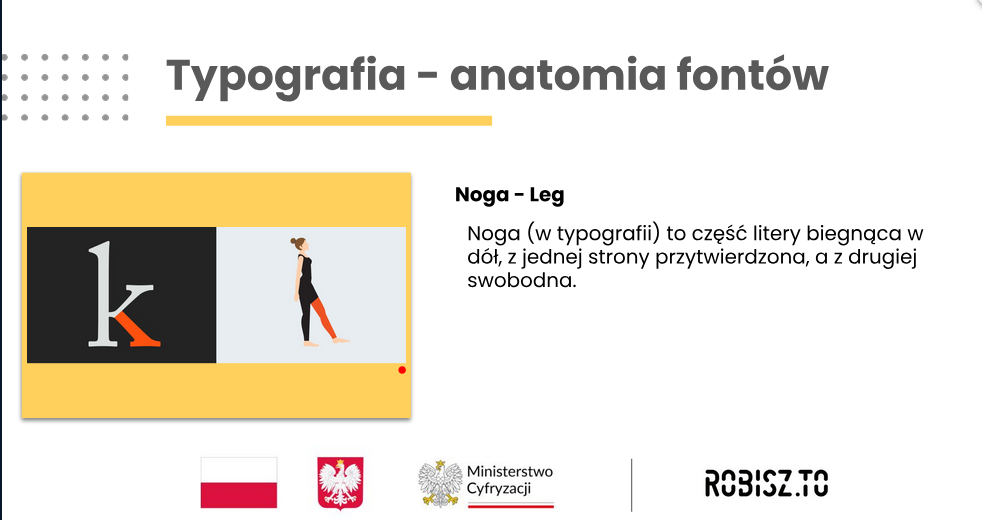
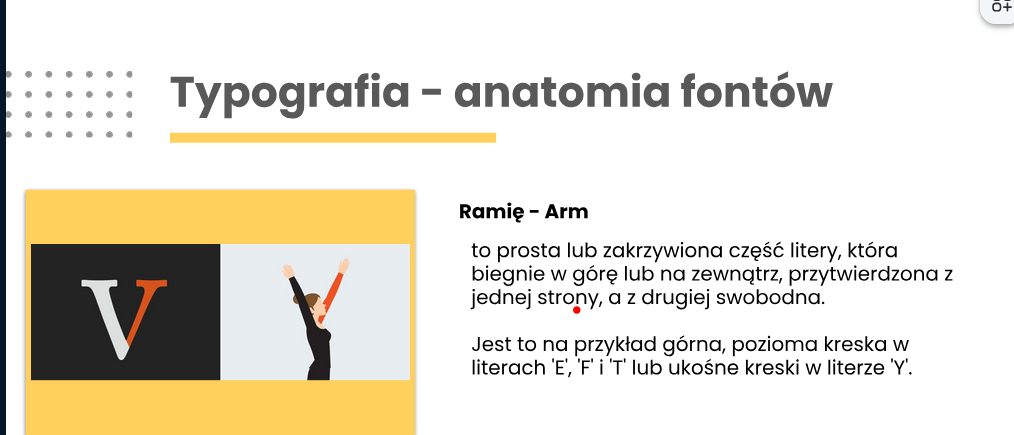
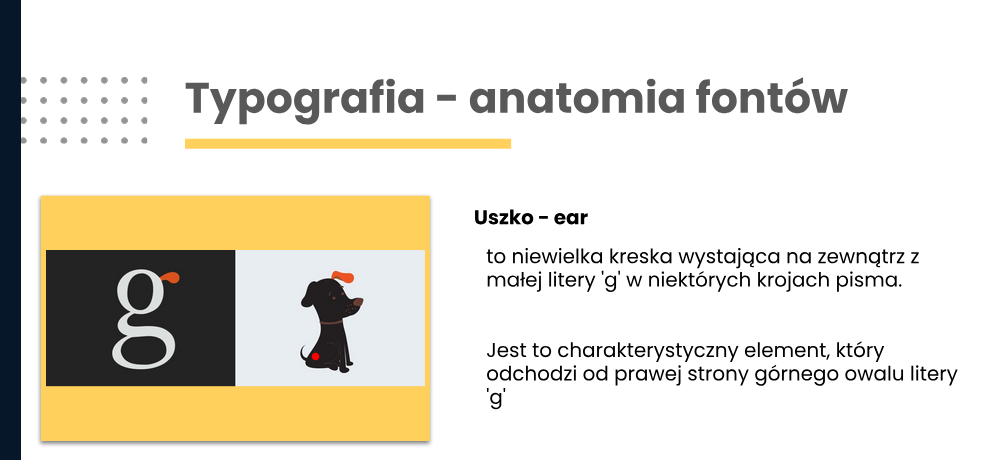
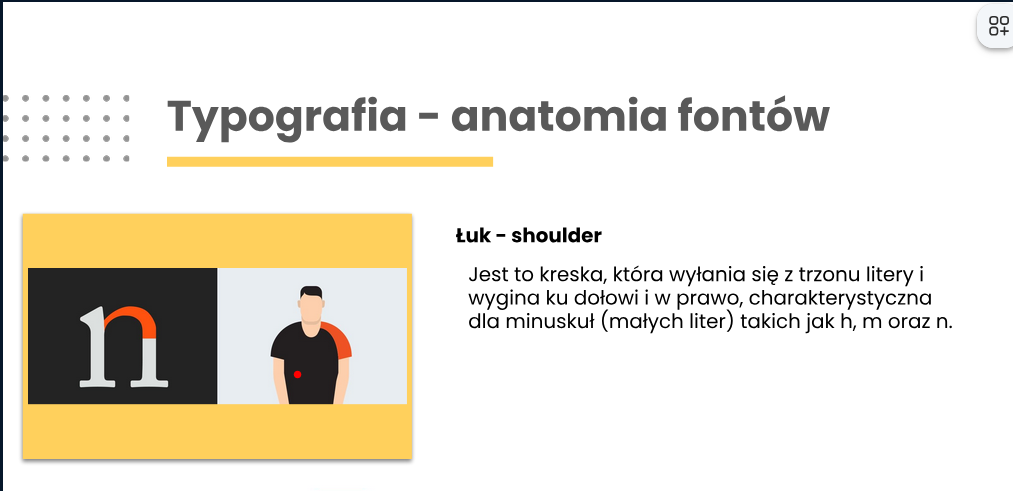
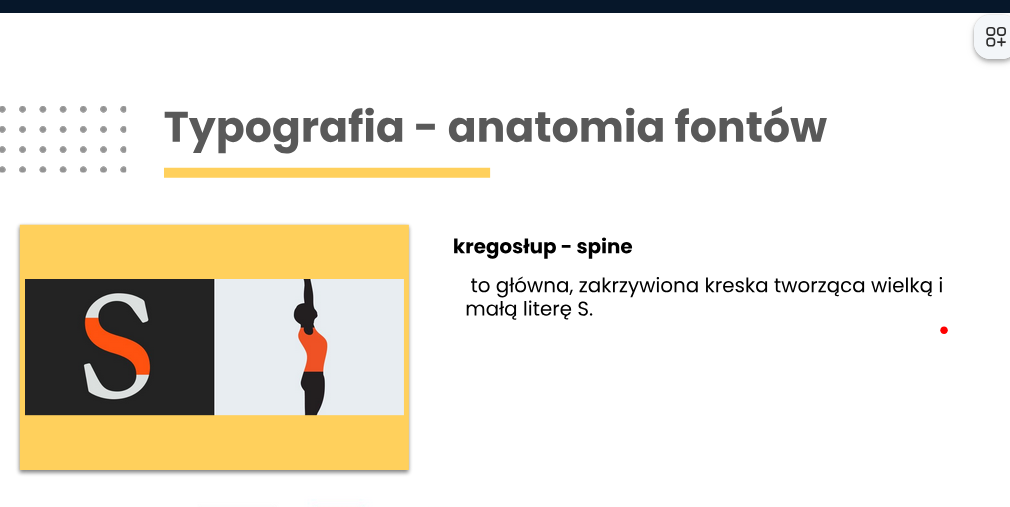
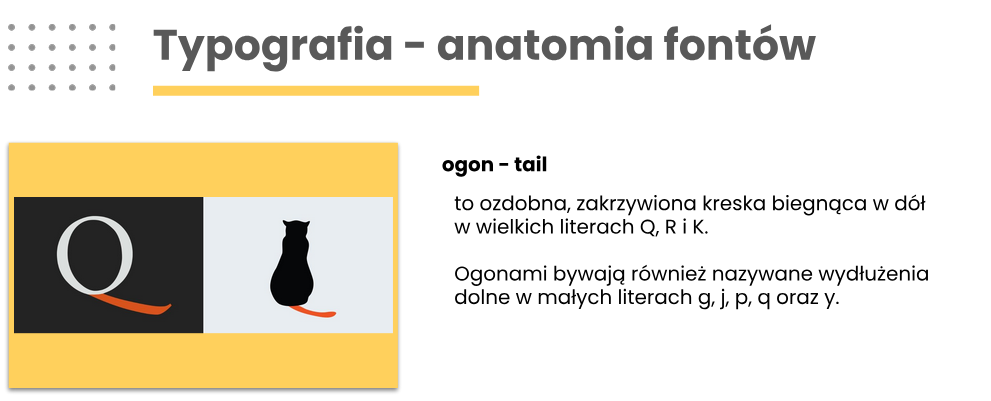
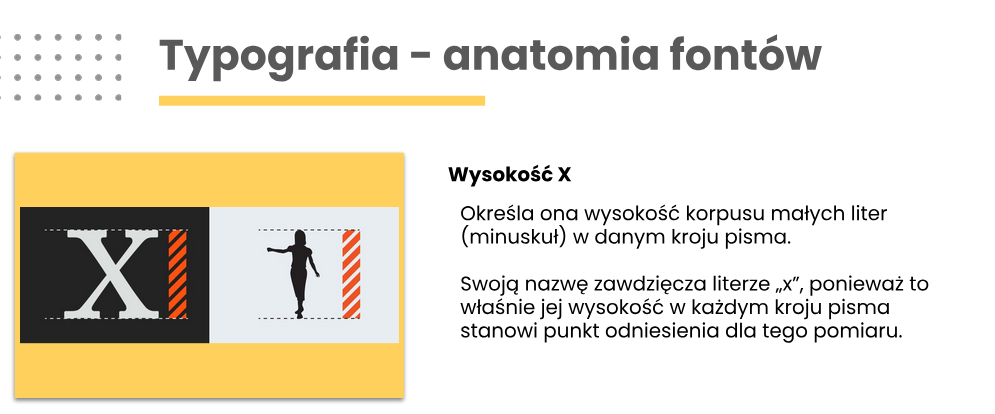
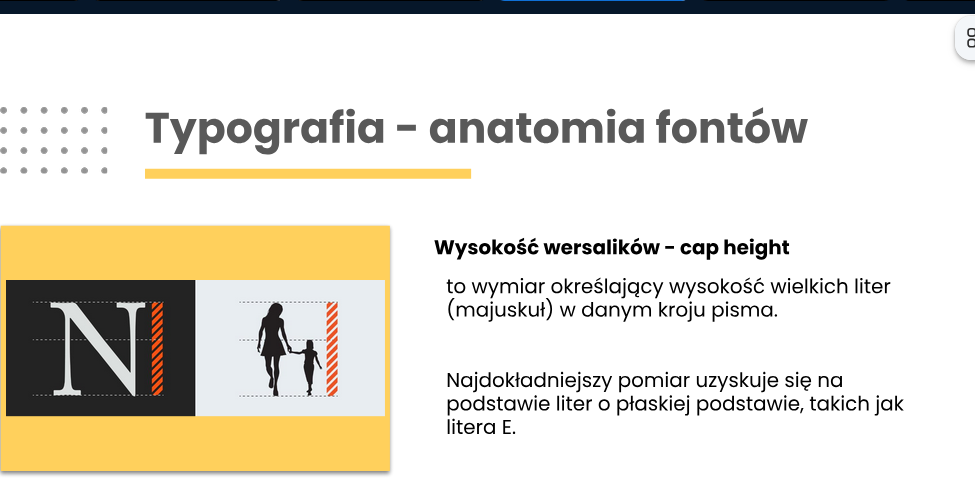
szeryfów będziemy suć
terminal/zakończenie w małym t przegapiłam
fonty szeryfwe uchodzą za eleganckie, są klasyczne, nagłówki, zaproszenia itp
Przykłady: Times New Roman, zaprojektowany dla The Times
Georgia, Garamond
do czytania na ekranie (szeryfowe w druku)
prostrze bezszeryfy są bardziej czytelne na monitorze, używa sę w aplikacjach, na tr internetowych, infografik itd
ale niektóre są używane w druku, by nie były za cienkie, bo papier ma strukturę i o druku może być nieczytelne
przykłady
Helvetica, arial, lato - tu ciekawostka,to polski fnt
trzeci rodzaj - fonty dekooracyje, tylko do naglówków, wyróżników, nie da się w tym przeczytać dłuzszego tekstu
przykłady:
Lobster, pacifico, Playball
Kerning to odstęp między literami a tracking między wyrazami
spacjapowinna mieć szerokosć taką, by zmieścić w nim małe "i"
Co decyduje o dobrym składzie?
dla mnie wysokość liter, justwanie, prost font, brak kerningów, lubię czarny tekst na białym tle
sieroty - i a na końcu wiersza
wdowy - krótkie słowa na końcu - na do ze
bękarty - kończy si akapit, przenosi się na nową stronę i na całąstrone mamy jedno czy dwa zdania
szewcy - kończy się strona i akapit się na niej zaczna - jedna linijka, niecałe zdanie
tych 4 unikamy
aplikacja do tworzenia własnych fontów:
Paleta kolorów
Wasz wybór
3. Typografia Logo / nagłówek: wielkość 40–60 pt.
Tekst prawny: 6–7 pt (min. 1,2 mm wysokości x‑a). inne: 14 pt
4. Key visual Coś kwaśnego
5. Tył – układ 3‑kolumnowy
Skład + ostrzeżenie
Tabela wartości (ramka 0,15 pt)
6. Kontrola jakości
Kontrast WCAG ≥ 4.5:1 dla tekstu < 18 pt.
Plik finalny: PDF/X‑4, 300 dpi, spady 5 mm
page tool narzędie strony - ostatnie narzędzie po lewej stronie
po kliknięciu zaznacza nam cała strone
możemy podać wartośc strony - np. a4, można ustawić marginesy
mozna dodać więcej stron
zadanie numer 2. artykul 2 stronicowy 2 kolumnowy z kilkoma zdjeciami o nowych technologiach
zadanie - artykuł o nowyc technlogiach ze wstawieniem zdjeć - zaimportowane jak na pierwszych zajęciach; alezy przejrzeć magazyny, zey zbaczyć, jak to wygląda w praktyce; pobawić się fontem - interlinią itd